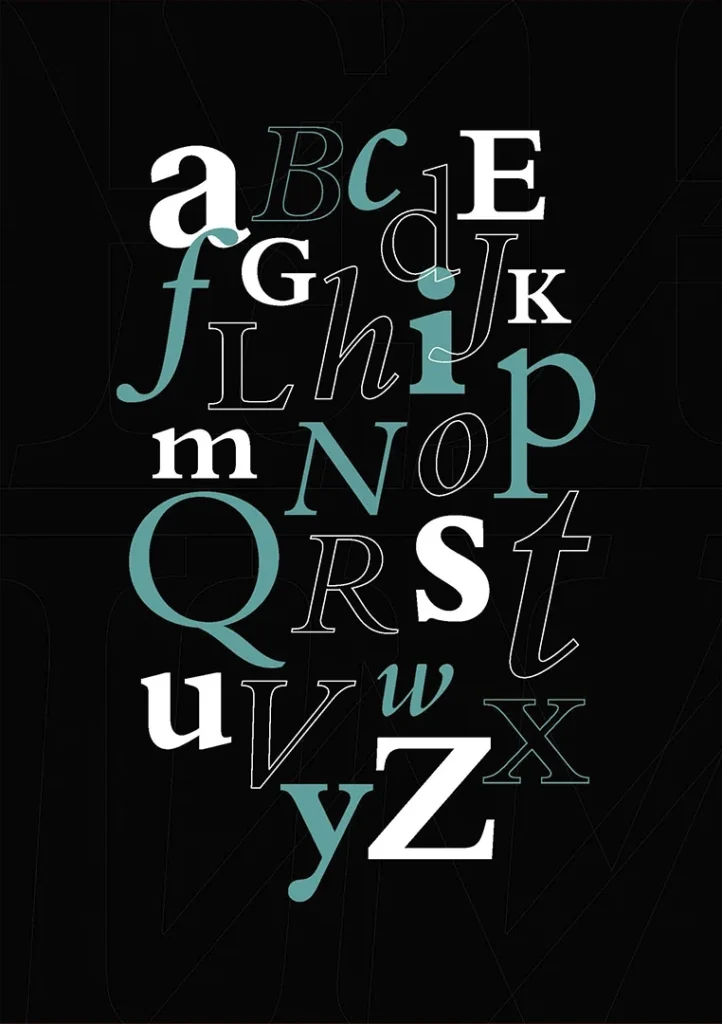
En 1929 la compañía inglesa Monotype, dirigida por entonces por Stanley Morison, se embarcó en un plan muy ambicioso para su época que fue el de volver a cortar numerosas tipografías históricas, entre los cuales la Bembo, que desde su lanzamiento se hizo muy popular para la composición de textos en libros.
Bembo es una Garalda o Romana antigua. Entre sus características más distintivas, podemos mencionar la cola de la “Q” comienza desde el centro del glifo, la “J” tiene un leve gancho y hay dos versiones de “R” mayúscula, una con cola recta y otra con cola curva y más extendida. Un espíritu caligráfico es particularmente evidente en los serifs, que muestran una delicada curva de transición que se se une con el bastón en cada letra.